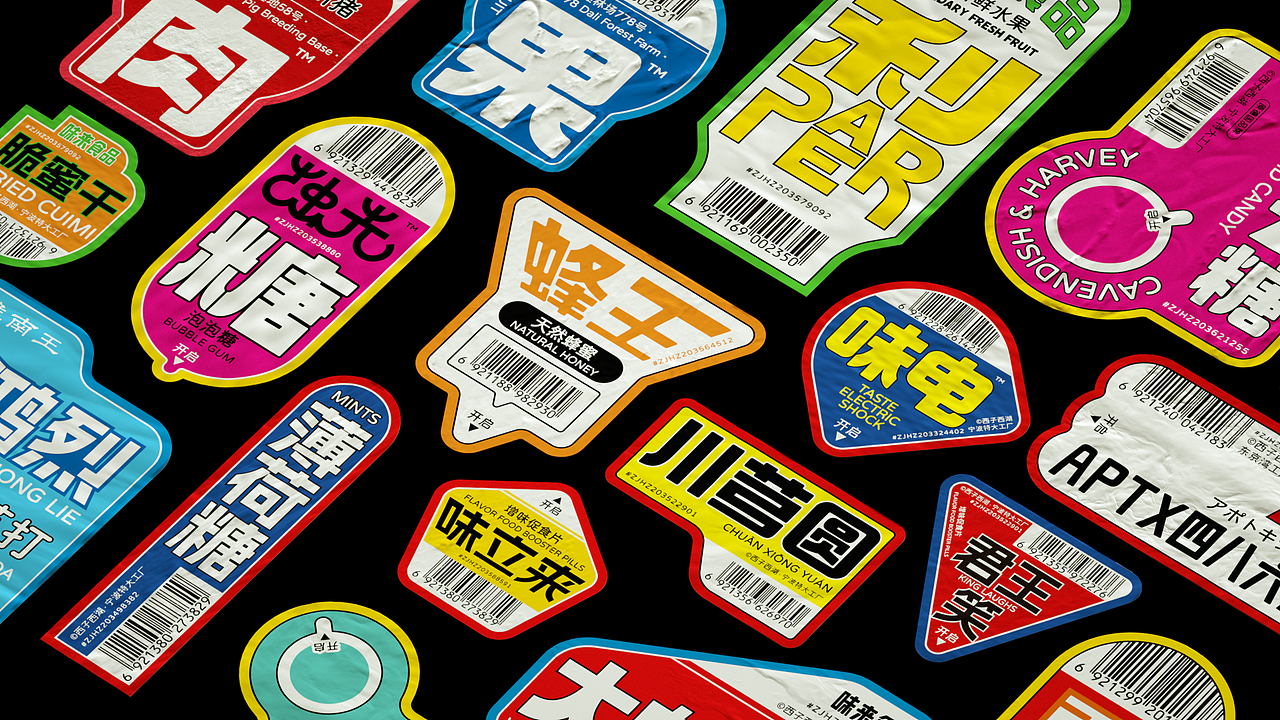
标签贴纸设计Label Sticker Design - #10~29
新概念复古标签
以“汉字”作为图形,以最直接的方式表达信息。摒弃其它装饰元素,将“汉字”图形化、装饰化、功能化,并融合80年代复古风格,创建一种既是过去也是未来的视觉风格。
字体:975 圆体、Aa厚底黑、LeeFont蒙黑体、阿里妈妈数黑体、标小智无界黑、OCR-B 10 Pitch BT、极影毁片荧圆、优设好身体、造字工房元黑体